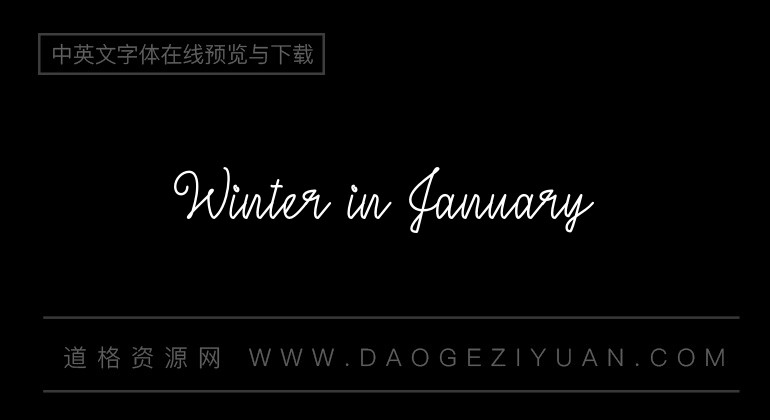
Winter in January
Winter in January(一月的冬天)是一种手写风格的字体,由女性插画师 Misti Hammers 创作。该字体具有流畅而舒适的笔触,具有自然、温暖和温馨的氛围。 Winter in January 字体有两种风格,分别是常规和斜体。它的字母形状是流畅的,字母之间有适当的间距,使得文字易于阅读。该字体适用于各种文本设计项目,例如宣传册、海报、包装设计、贺卡等。 此外,Winter in January 字体支持多种语言,包括英语、西班牙语、德语、法语、意大利语等。可以通过多种方式获得该字体,例如从字体商店购买、免费下载或订阅字体服务。
Winter in January是一款非常不错的手写艺术字体,具有很好的视觉感,适合于文化类的宣传设计、商业类品牌的广告和产品包装设计以及个性化文字排版等较多场景。